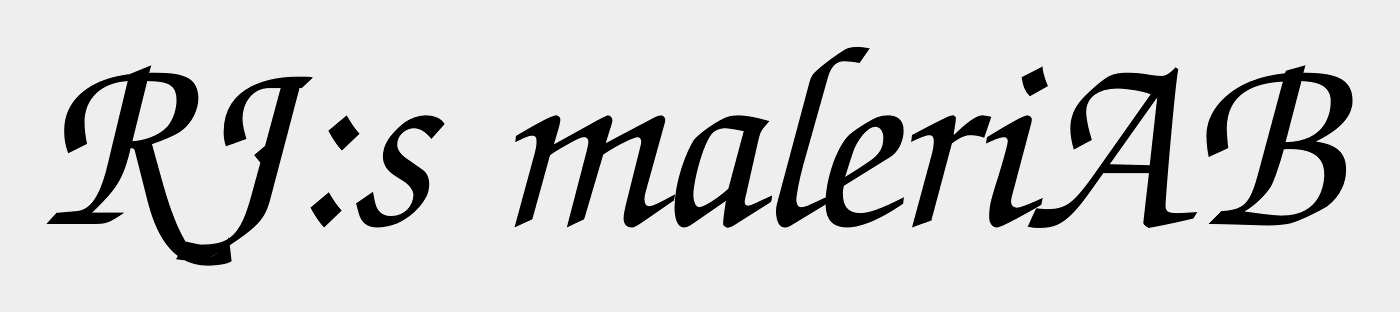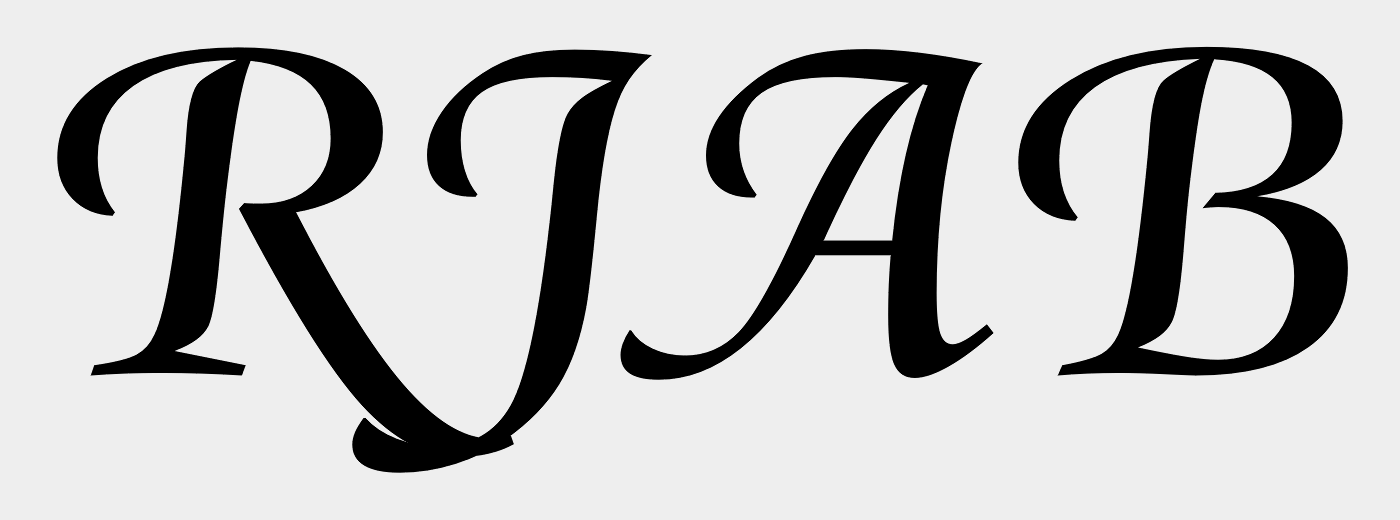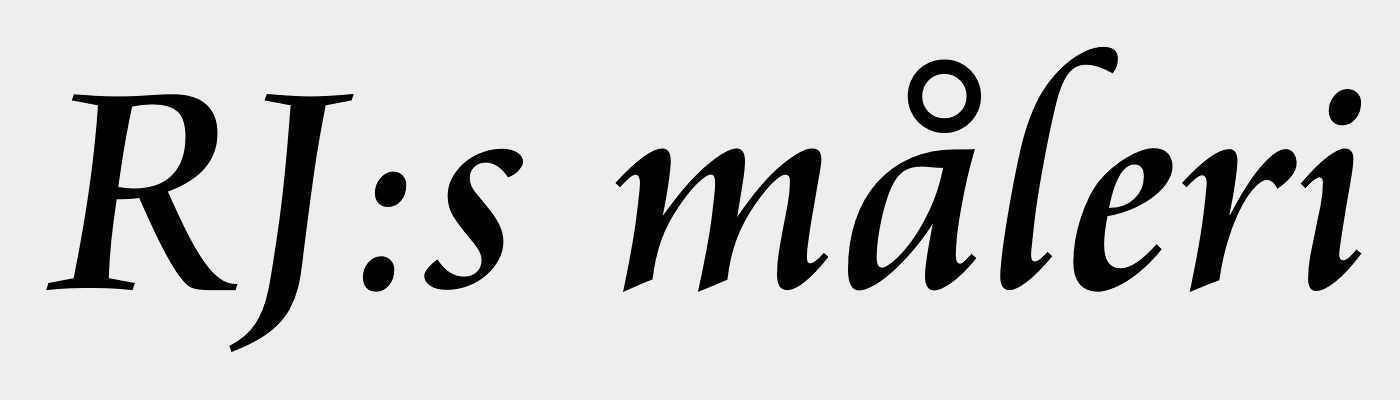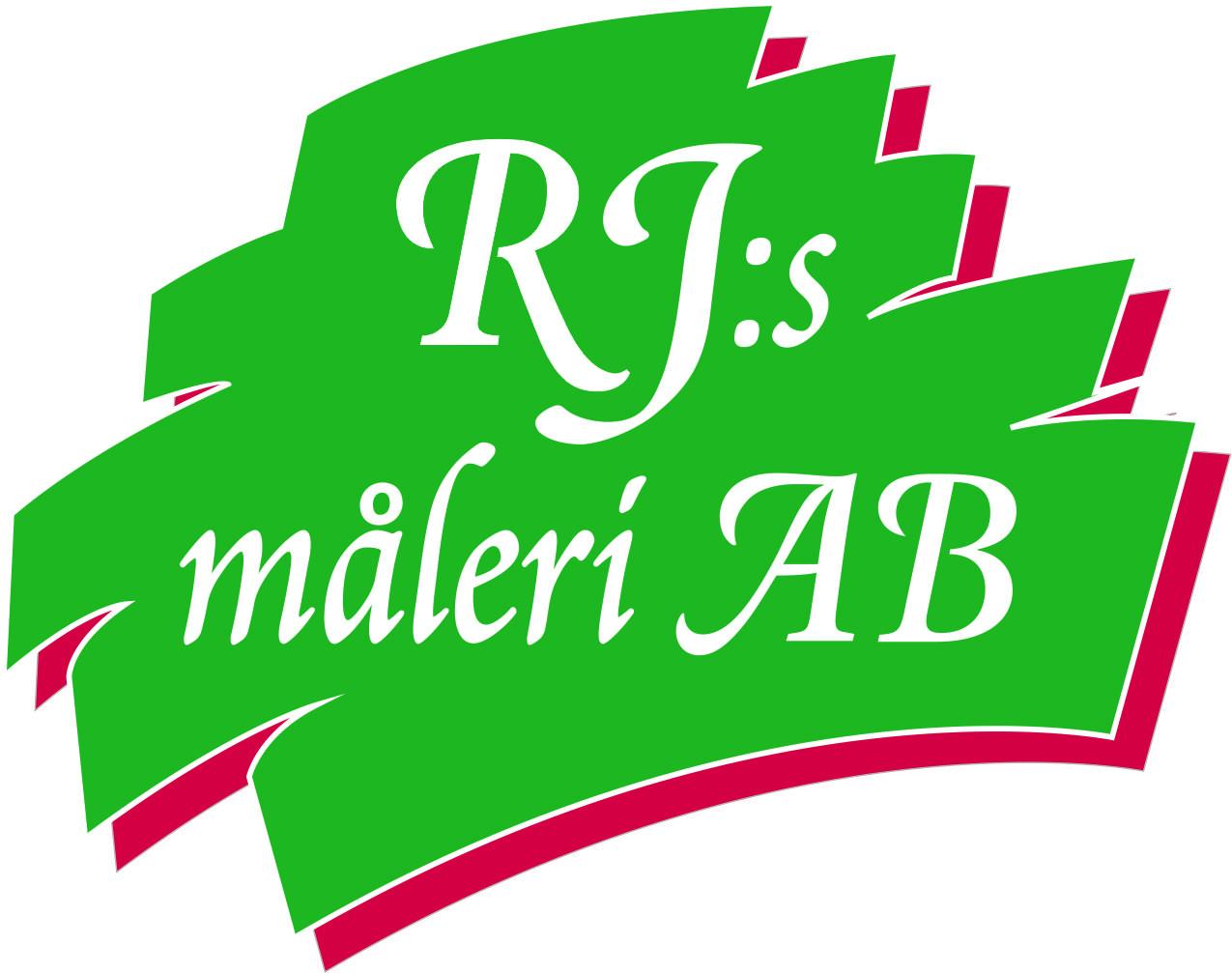
Schwedische Malerfirma "RJ:s måleri" - Wie heisst die Schriftart?
Eine kleine värmländische Malerfirma möchte ergänzende Texte auf dem Schaufenster in ihrer Logo-Schriftart haben.
Ich komme mal wieder nicht darauf, obwohl ich meine, dieser Schriftart schon so oft über den Weg gelaufen zu sein.
Hat jemand vielleicht spontan den Namen zur Hand bzw. im Kopf?
Die Cataneo gibt es schon auch mit Swashes:
Sieht aber im Detail trotzdem leicht anders aus.
Gelöst! Das reicht absolut - Ihr seid meine Helden! Cataneo habe ich natürlich bereits installiert, mit und ohne Swashes 🙂